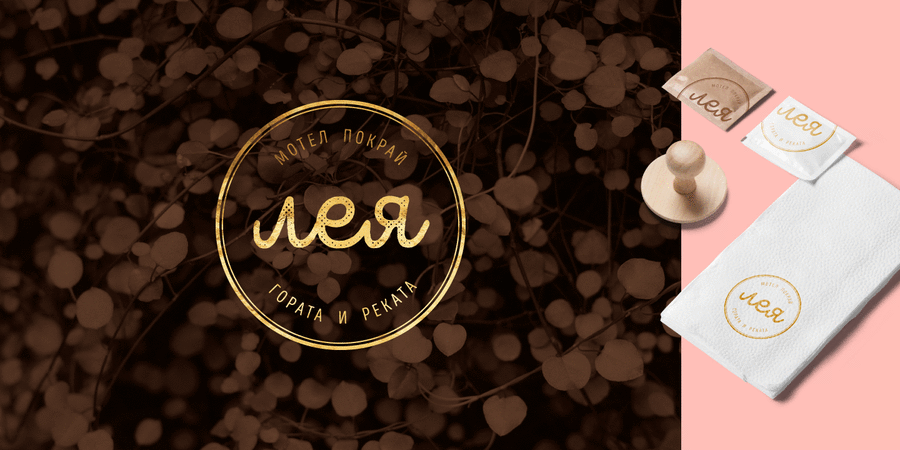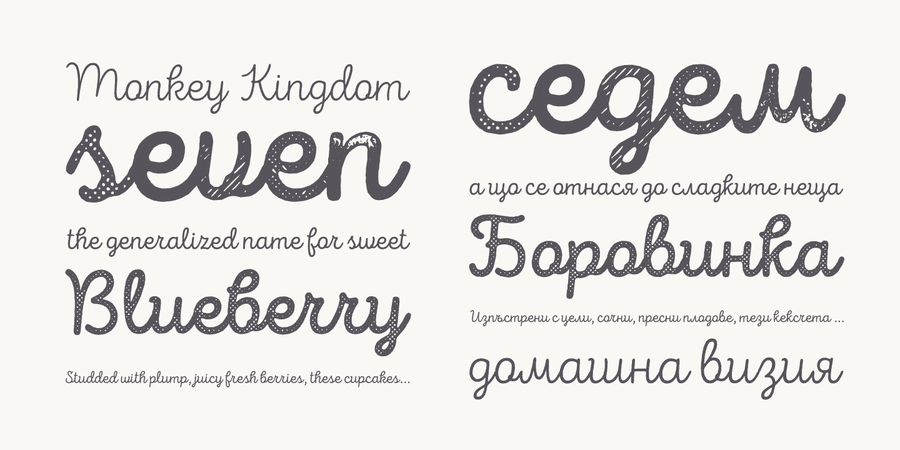
Бесплатное рукописное начертание одной из крупнейших шрифтовых систем в мире Интро Раст, включающей 214 начертаний. Это огрубленная текстурная версия известного шрифта Интро. Система Интро Раст включает 4 семейства: Intro Rust, Intro Script, Intro Head и Intro Goodies. Она может применяться для создания почти всех видов дизайнерской продукции от полиграфии до веб-дизайна. Просто используйте воображение и ваши проекты станут более живыми, благодаря шрифтам системы Интро Раст. Хотите сделать поздравительную открытку или дизайн упаковки или даже айдентику? Смело экспериментируйте с паттернами и рисунками, рукописными версиями или теми классными начертаниями с точками и получайте современный успешный дизайнерский проект. Шрифт разработан Светославом Симовым, Ани Петровой и Радомиром Тинковым в 2015 году и выпущен фирмой Фонтфабрик. http://www.fontfabric.com/intro-rust/
Асоціації з сімейством шрифтів Intro Script R H2 BaseОсобистість і характер гарнітури:
хіпстерський, вінтажний, побутовий, смачний, старомодний, добрий, наївний, милий, М'який, ремісничий, чесний, рукотворний, ручний, ностальгічний, екологічний, доброзичливий, довірчий, зелений, натуральний, природний, теплий, ламповий, апетитний, здоровий, гнучкий, модний, грайливий, потішний, прикольний, привітний, красивий, свіжий, характерний, акуратний, мотузковий, круглий, сільський, бадьорий, святковий, соковитий, стиглий, фермерський, домашній, крафтовий, літній, симпатичний, артізанальний, рослинний, лісовий
торгівля, продукти, ремесло, хенд мейд, ярмарок, кафе, фаст фуд, закуска, їжа, відпочинок, крамниця, фермер, одяг, взуття, природа, піцца, десерт, море, пляж, розваги, свято, табір, школа, дитяча книжка, подарунки, кондитерська, булочна, сік, торт, квіти, щоденник, зошит, ферма, прикраса, кава, селфі, Хюґе, смузі, Інстаграм, графіка, ілюстрація, учень, школяр, дім, побут Гарнітура має ознаки стилів: